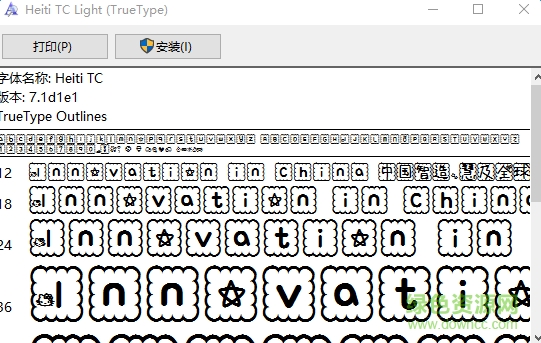
童趣小餅干字體是一款很有個性的電腦藝術字體,這款字體也正是因為有著獨特的魅力,所以很多年輕人都喜歡用這款字體,如果你也喜歡的話可以隨時來綠色資源網(wǎng)下載。
童趣小餅干字體是一款很不錯的電腦字體,寫出來的字非常好看,小編已經(jīng)幫大家試用過了,歡迎大家來綠色資源網(wǎng)下載。